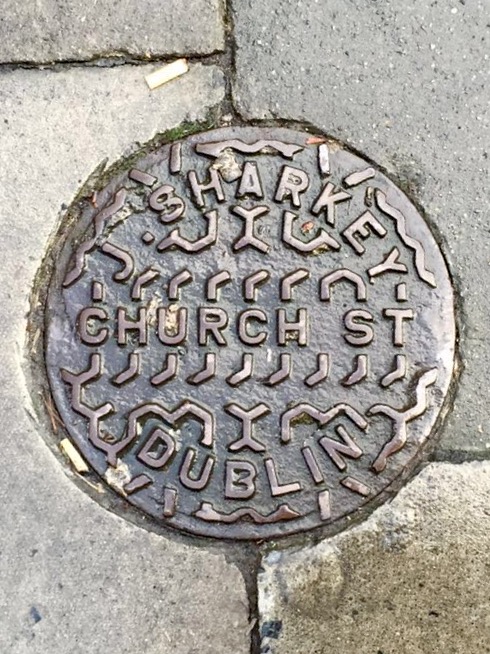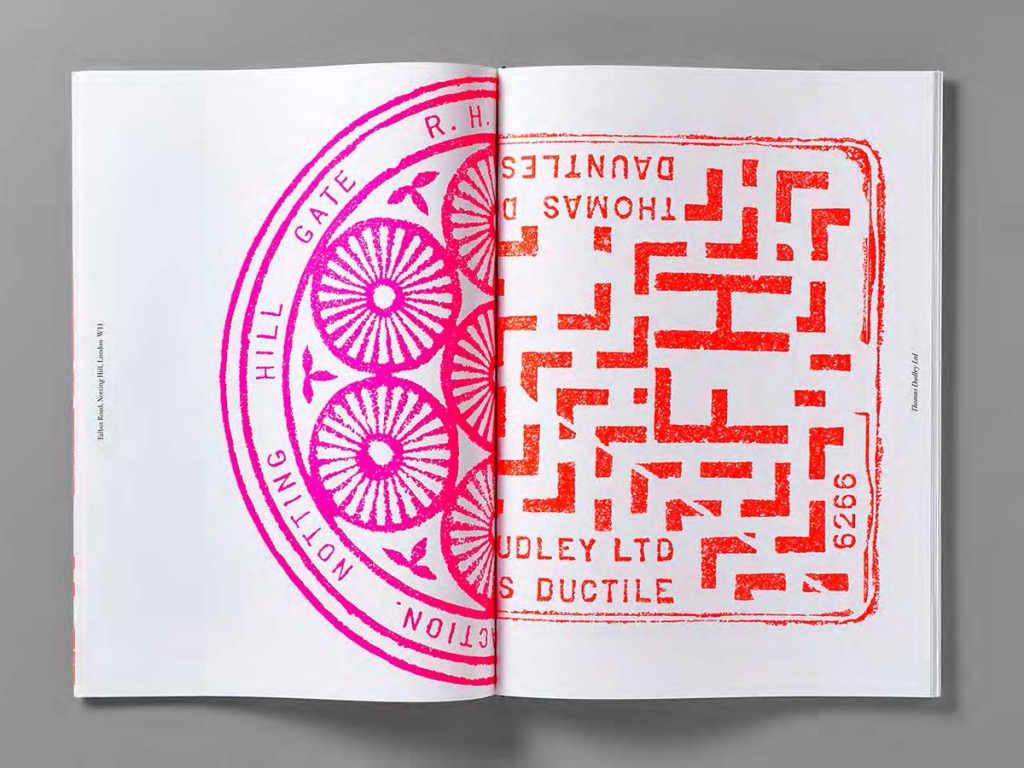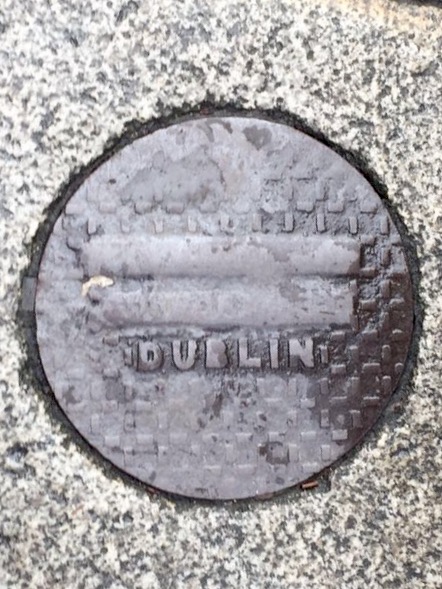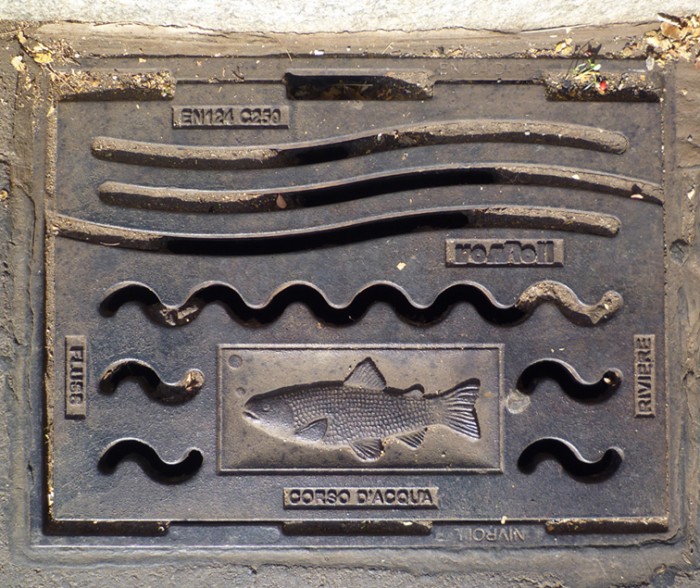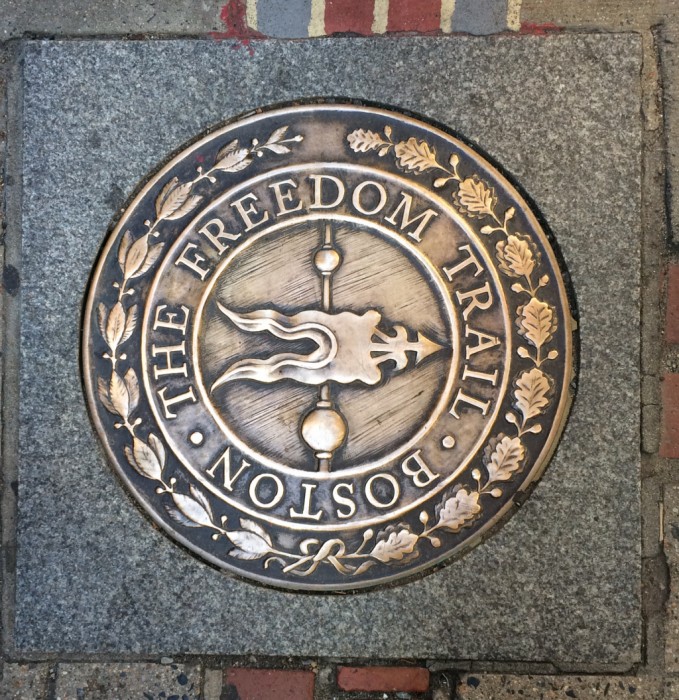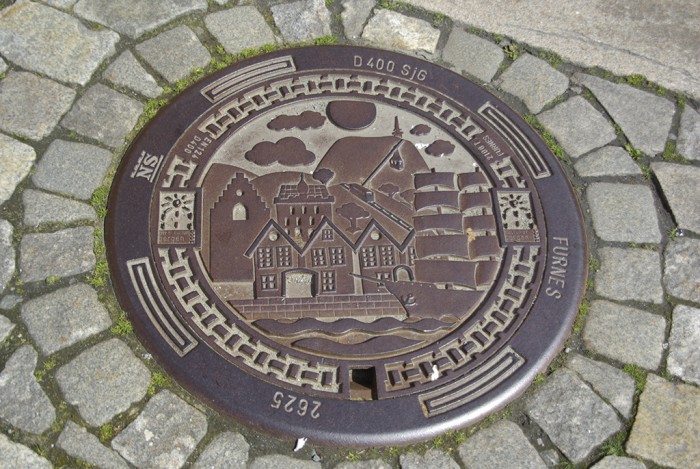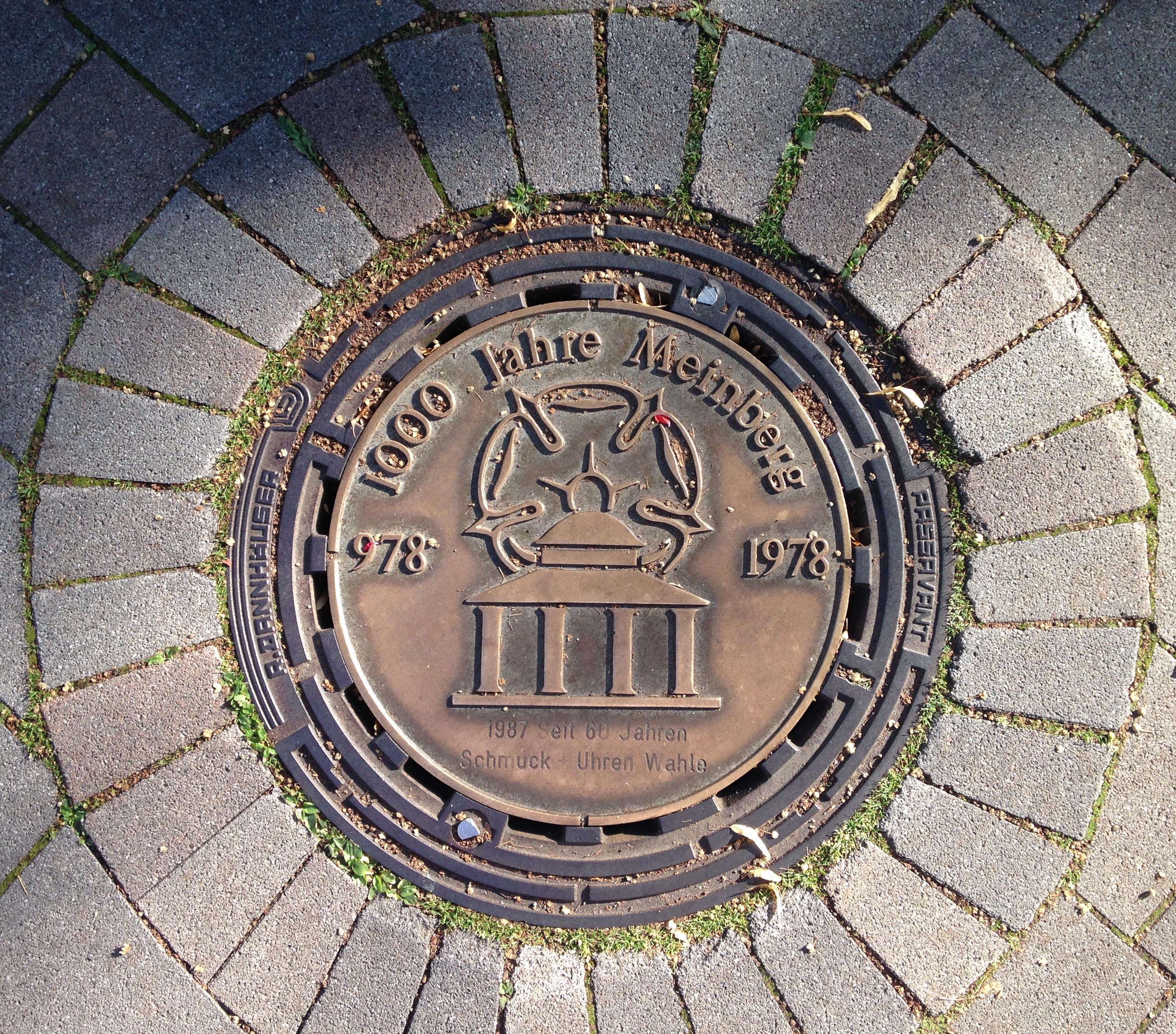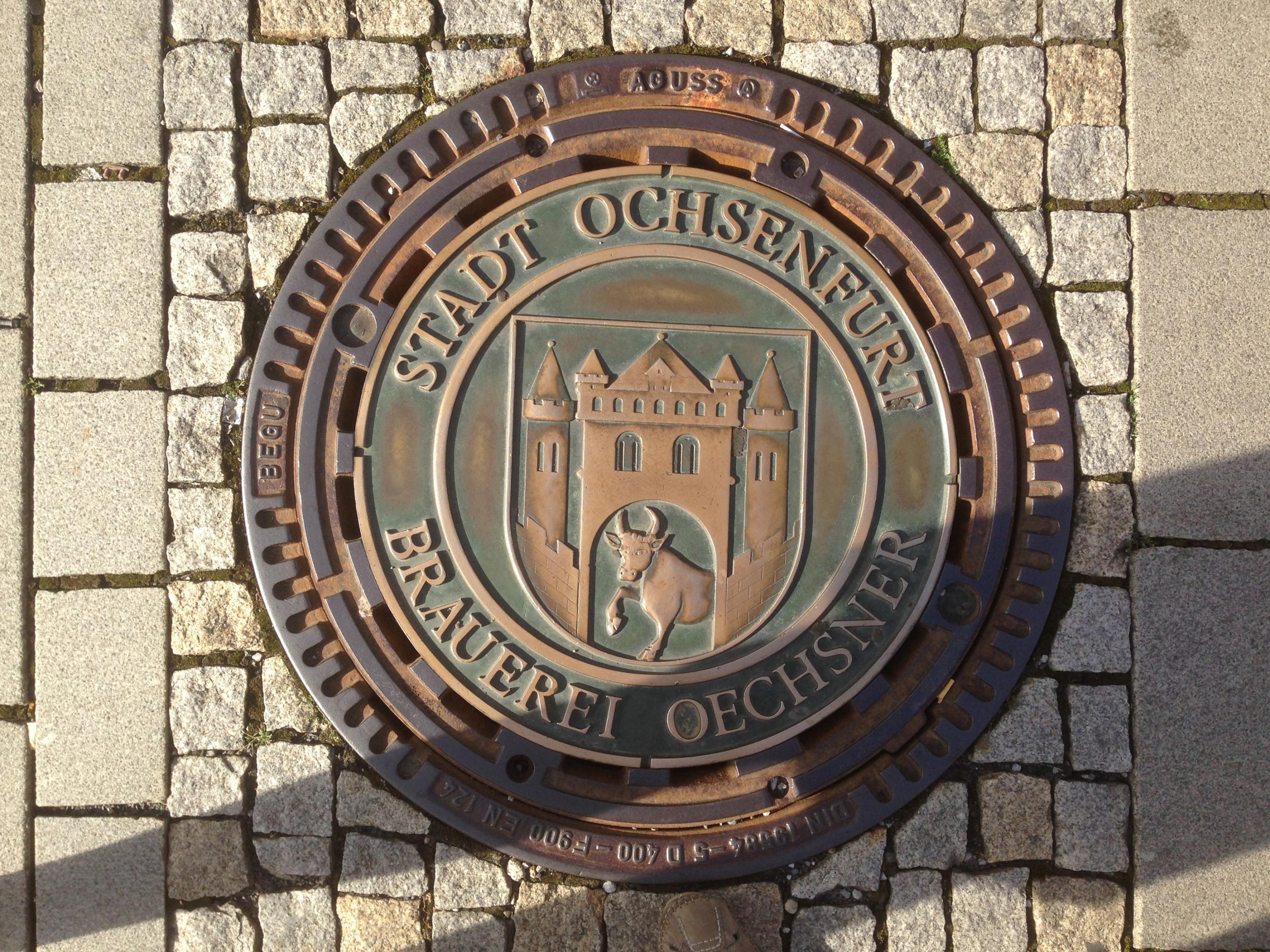
[Mitglied Tobi…] Geschrieben August 31, 2015 Teilen Geschrieben August 31, 2015 Ich hab’s leider selber nicht gesehen, aber ein Bekannter erzählte mir neulich von einem Künstler, der hier in Osnabrück Gullideckel mit Farbe bestreicht und das Motiv dann auf ein T-Shirt druckt, also vielleicht sollten die Drain-Spotter unter uns demnächst mit nem Farbeimerchen, ner Walze und nem weißen T-Shirt statt Kamera auf die Jagt gehen Die Aktion ist Teil des Projektes Stadtvermessung 2015, allerdings gibt es auf der Seite zu der genannten Aktion keine weiteren Infos oder Bilder … Link zu diesem Kommentar
[Mitglied Pach…] Geschrieben September 1, 2015 Themen-Ersteller Teilen Geschrieben September 1, 2015 Ja, es gibt da verschiedene Techniken, Axel Fischer z. B. reibt sie durch, andere verwenden sie mit Farbe klassisch wie eine Hochdruckform. Auf den Typotagen hatte ich mal einen Typographie-Dozenten getroffen, der das mit seinen Studenten gemacht hat. Der hat dann auch eine Postkartenserie mit den Deckel-Drucken herausgegeben. Link zu diesem Kommentar
[Mitglied Kath…] Geschrieben September 1, 2015 Teilen Geschrieben September 1, 2015 Schöne Ideen. Link zu diesem Kommentar
[Mitglied Kath…] Geschrieben September 30, 2015 Teilen Geschrieben September 30, 2015 Der Bund der Steuerzahler prangert Verschwendung an: (…) Die Gemeinde Wallenhorst im Landkreis Osnabrück wollte (…) mit illuminierten Gullydeckeln für Glanz sorgen: Inmitten des überfahrbaren Kreisverkehrs sollten fünf Gullys mit bunten LED-Lichtern versehen werden, beschloss der Gemeinderat im vergangenen Jahr. Rund 10.000 Euro wurden in Lichttechnik und Leuchtmittel investiert. Doch das Licht leuchtet so schwach, dass schnell der Name „Glühwürmchen-Kreisel“ in der Gemeinde geboren war. Ein Bild eines solchen Gullideckels gibt es hier. Link zu diesem Kommentar
[Mitglied Þors…] Geschrieben September 30, 2015 Teilen Geschrieben September 30, 2015 Ich finde ja, dass Deutschland deutlich mehr Kunst im öffentlichen Raum gebrauchen könnte. Das können andere Länder deutlich besser. Link zu diesem Kommentar
[Mitglied Tobi…] Geschrieben September 30, 2015 Teilen Geschrieben September 30, 2015 In der Nachbargemeinde (kleiner Ort, genauer ein Flecken) meiner Eltern hat man ne halbe Million für einen Kreisel ausgegeben, um dann nach Fertigstellung festzustellen, dass die Busse den leider nicht passieren können … die fahren jetzt ne krude Umleitung. Das ist doch auch ne Kunst irgendwie Hatte ich erwähnt, dass der Kreis an dieser stelle so oder so keinen Sinn gemacht hat? Und diese großen Freiluft-Installationen über die Absurdität der öffentlichen Hand, die über all sind, reichen nicht als Kunst? Wie hießen die noch gleich … achja BER und Elbphilharmonie Link zu diesem Kommentar
[Mitglied Thom…] Geschrieben Oktober 19, 2015 Teilen Geschrieben Oktober 19, 2015 Beim Ausmisten meiner Fotos habe ich diese Aufnahme von 2012 gefunden. Ich weiß nicht, ob ich den Deckel schon gepostet hatte – wollte jetzt aber auch nicht dreiundzwanzig Drain-Spotter-Seiten durchschauen. Pachulke, ein Kick auf das Bild führt dich zum großen Foto, das du gerne für die Manholecover-Seite benutzen kannst. 1 Link zu diesem Kommentar
[Mitglied Pach…] Geschrieben Oktober 19, 2015 Themen-Ersteller Teilen Geschrieben Oktober 19, 2015 ¡Muchas Gracias! Link zu diesem Kommentar
[Mitglied Pach…] Geschrieben Oktober 19, 2015 Themen-Ersteller Teilen Geschrieben Oktober 19, 2015 Kursive Versalien im Rundsatz ist aber auch … mutig. Link zu diesem Kommentar
[Mitglied Stef…] Geschrieben Oktober 29, 2015 Teilen Geschrieben Oktober 29, 2015 "The Freedom Trail" in Boston (ist zwar kein Kanaldeckel, aber trotzdem schön) 1 Link zu diesem Kommentar
[Mitglied Erwi…] Geschrieben Oktober 31, 2015 Teilen Geschrieben Oktober 31, 2015 letzthin gefunden in Winterthur 2 Link zu diesem Kommentar
[Mitglied Kath…] Geschrieben November 3, 2016 Teilen Geschrieben November 3, 2016 Die Gullideckelbande ist geschnappt. (Freund Pachulke wird die Verfehlung der jungen Leute vermutlich aufs Hamburger Schulsystem zurückführen … ;-)) 1 Link zu diesem Kommentar
[Mitglied 17b4…] Geschrieben November 4, 2016 Teilen Geschrieben November 4, 2016 Ach, ich hatte da ja noch was aus dem Urlaub mitgebracht: Falls schon bekannt und vorhanden, ignorieren, falls noch nicht darf es natürlich gerne für die Sammlung verwendet werden. Link zu diesem Kommentar